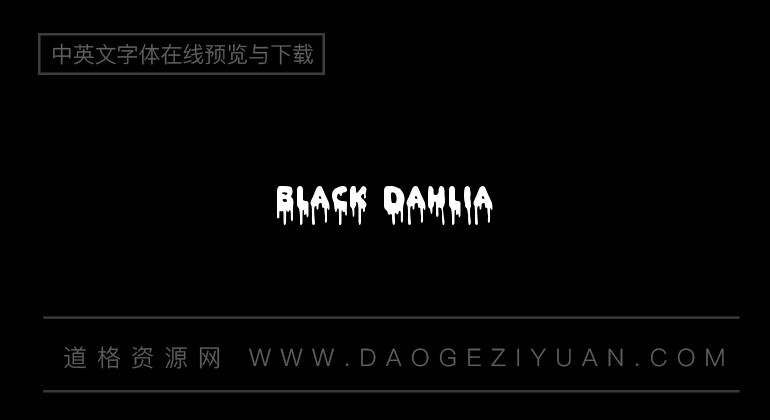
Black Dahlia
Black Dahlia 字体是一种黑体字体,具有明显的现代感和艺术感。该字体的名称源自于1947年发生在美国的一宗著名谋杀案,这使得该字体在设计界具有一定的文化背景和历史意义。 Black Dahlia 字体的设计风格特点是线条粗细不均,笔画粗犷而有力,同时还有一些特殊的设计元素,如字母中间的空洞和点缀等。 由于其独特的设计风格和历史意义,Black Dahlia 字体在广告、海报、书籍封面等设计领域中得到了广泛的应用。同时,该字体也适用于一些需要强调独特性和现代感的设计项目中。
Black Dahlia是一款非常不错的手写艺术字体,具有很好的视觉感,适合于文化类的宣传设计、商业类品牌的广告和产品包装设计以及个性化文字排版等较多场景。